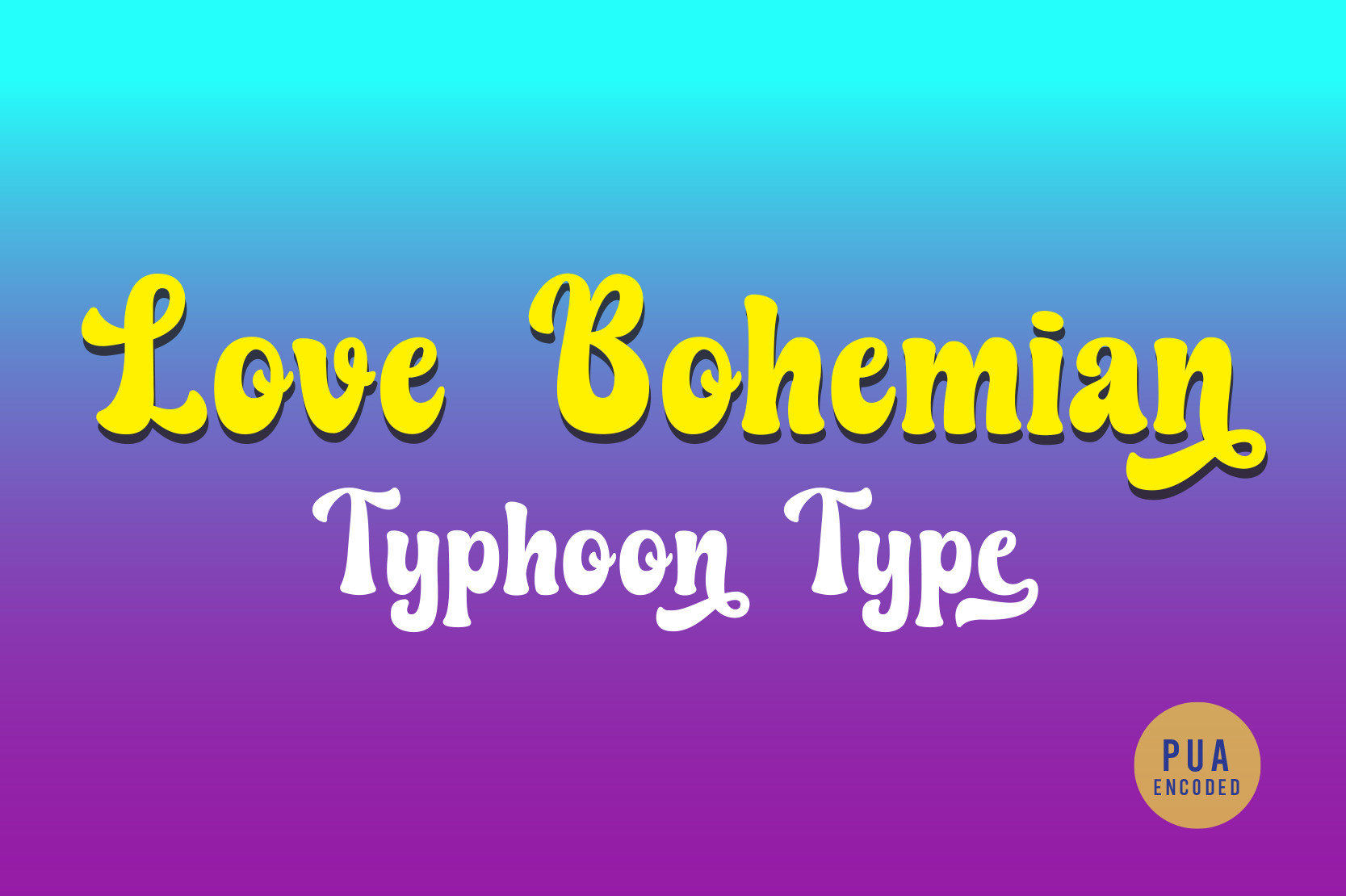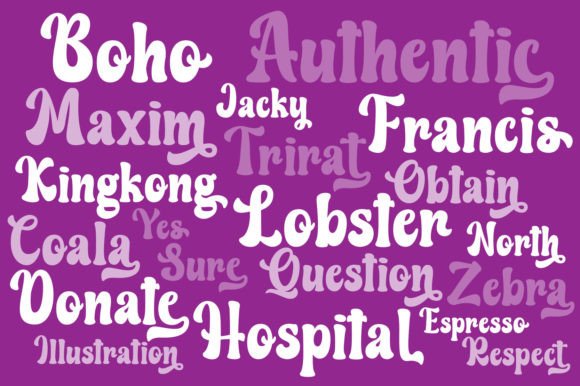
| ⭐ توضیحات | Love Bohemian یک فونت انگلیسی فریبنده است که جوهره سبک groovy را در خود دارد. این فونت که برای متمایز شدن از دیگران طراحی شده است، جذابیت مقاومت ناپذیری دارد که برای انواع پروژه های تبلیغاتی عالی است.
Love Bohemian با ظاهر منحصر به فرد و بازیگوش خود، به هر طرحی حسی از شیفتگی می بخشد. حروف سیال و منحنی آن یک جریان هماهنگ ایجاد می کند که بدون زحمت چشم را جلب می کند. چه یک تبلیغ چاپی، چه کمپین دیجیتال، یا هر تلاش تبلیغاتی دیگری، Love Bohemian انتخاب ایده آلی برای القای فضایی لذت بخش و فریبنده است که تاثیری ماندگار بر جای می گذارد. به راحتی آب می خورد! |